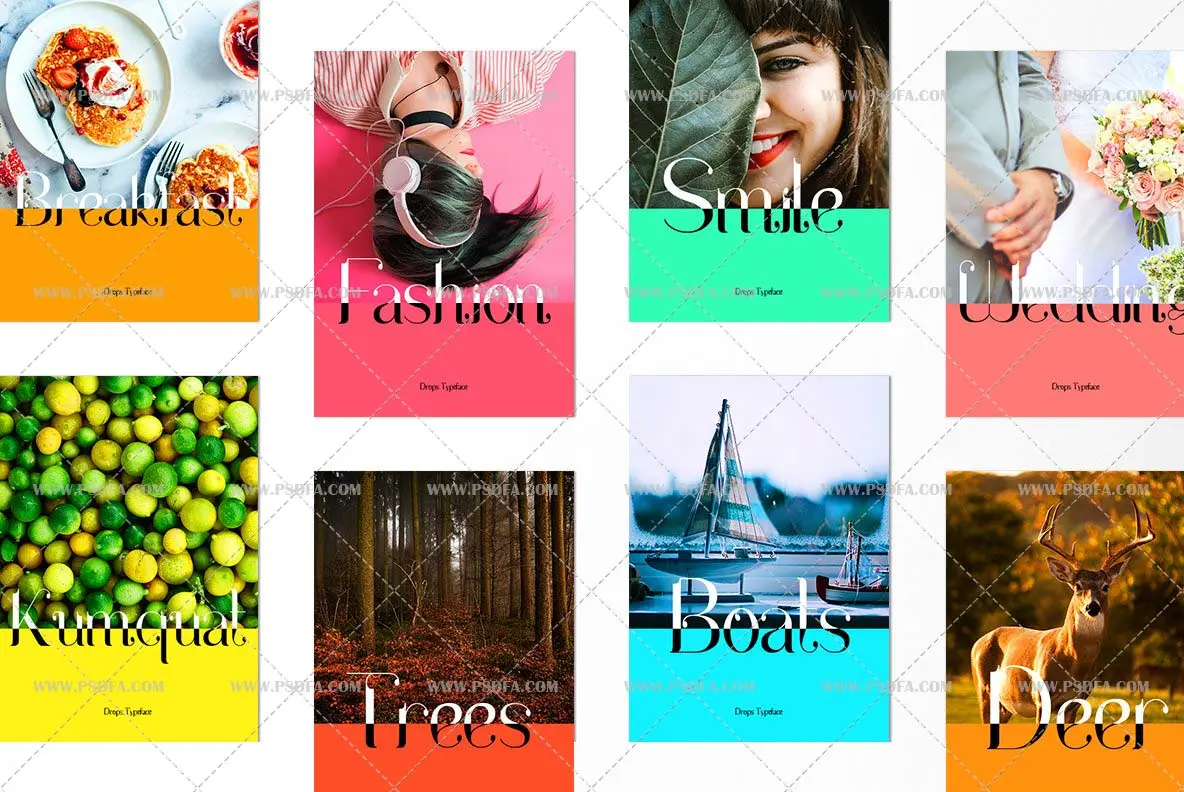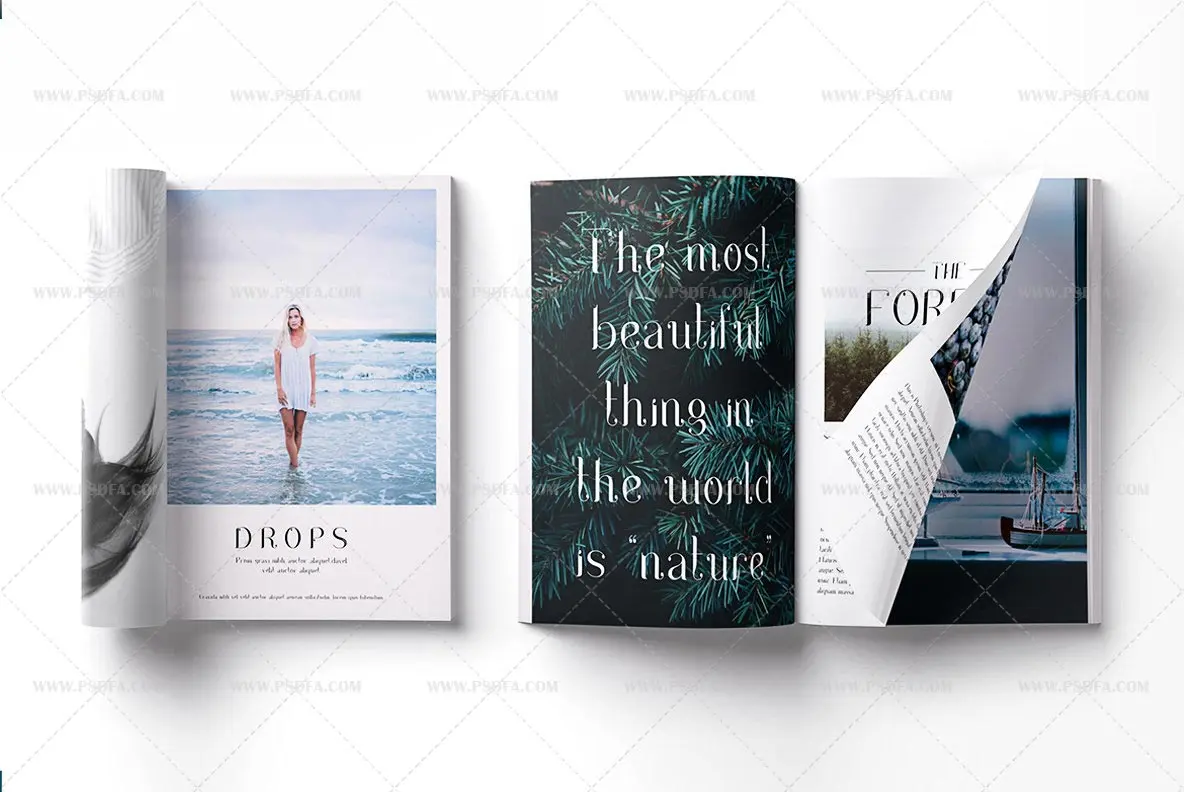
فونت انگلیسی قطره
در این مطلب شاهد یکی دیگر از فونت های زیبای انگلیسی با نام فونت انگلیسی قطره می باشید. این فونت زیبا در دو فرمت OTF و TTF در فایل فشرده موجود است که پس از خارج کردن فایل از حالت فشرده و نصب فونت ها در سیستم می توانید از آن ها در تمام نرم افزارهای گرافیکی و ویرایش متن استفاده کنید. فونت Drops یا همان قطره که از کیفیت بالایی نیز برخوردار است دارای شکل و حالت قطره می باشد که پیش نمایش آن را می توانید در تصاویر زیر مشاهده فرمائید. از این فونت می توان در طراحی لوگو ، طراحی ظروف ، طراحی لباس و پارچه ، طراحی انواع کارت های هدیه ، کارت دعوت ، کارت پستال ، کارت ویزیت ، طراحی روزنامه یا مجله ، طراحی انواع پوستر و صدها ایده دیگر استفاده نمود. امیدواریم این فونت مورد رضایت شما قرار گیرد و در طرح های گرافیکی خود از آن استفاده کنید.